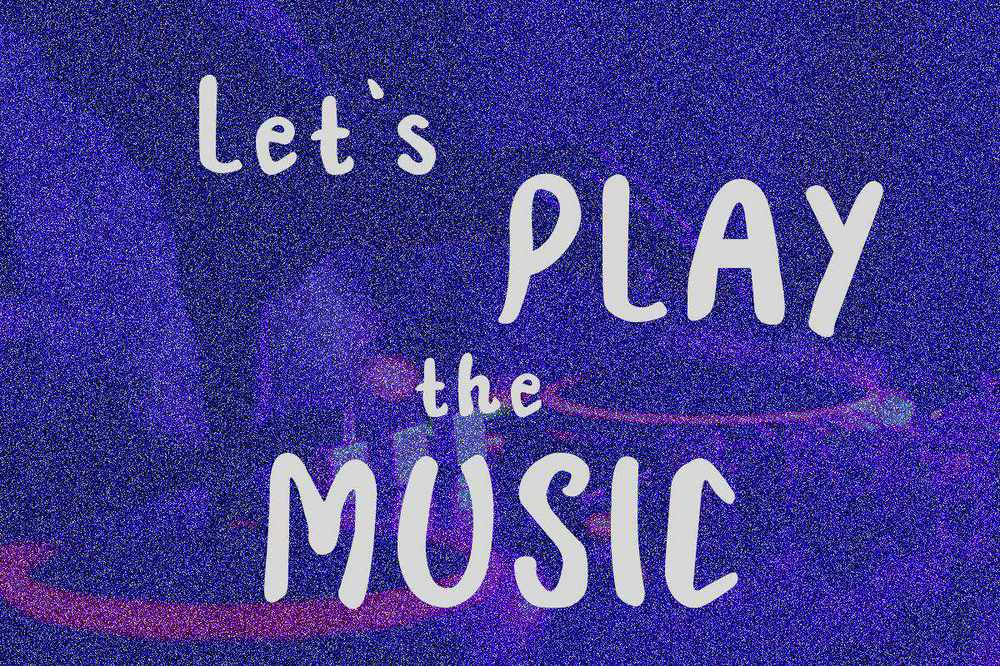
CellavieisAdisplayFont具有自然的感觉和友好性,适用于您的商业项目,如Go、婚礼设计、社交媒体、广告、产品包装、产品设计、标签、摄影、水印、邀请函、文具和需要童年、冒险、嬉戏和自然品味的项目。CellavieisAdisplayFont具有自然的感觉和友好性,它适用于您的商业项目,如Go、婚礼设计、社交媒体、广告、产品包装、产品设计、标签、摄影、水印、邀请、文具和需要童年、冒险、嬉戏和自然品味的项目。